ฟอนต์เว็บไซต์ที่ดีที่สุดและวิธีเลือกฟอนต์ที่เหมาะสม
เผยแพร่แล้ว: 2022-02-11ตั้งแต่โทนสีไปจนถึงฟอนต์และการออกแบบชื่อเรื่อง ทุกรายละเอียดเล็กๆ น้อยๆ มีความสำคัญหากเรากำลังพูดถึงโปรเจกต์ดิจิทัลขนาดใหญ่อย่างเว็บไซต์ของคุณ การใช้ฟอนต์และเอฟเฟ็กต์ฟอนต์ที่แตกต่างกันอาจส่งผลทั้งด้านลบและด้านบวกต่อผู้ใช้ของคุณ และขึ้นอยู่กับคุณว่าจะเป็นด้านบวกหรือด้านลบ ความสมดุล วิธีการที่สอดคล้องกันในการเชื่อมโยงรายละเอียดทั้งหมดเหล่านี้ให้เป็นงานสร้างสรรค์ที่มีการจัดระเบียบเป็นอย่างดี มีความสำคัญยิ่งสำหรับนักออกแบบดิจิทัลทุกคน
ฟอนต์และเอฟเฟ็กต์ฟอนต์คือวิธีที่ดีที่สุดในการบรรลุความสมดุลนั้น เพราะสำหรับเว็บเพจส่วนใหญ่ ข้อมูลภาพจำนวนมากที่สุดจะถูกครอบครองโดยข้อความเนื้อหา ชื่อเรื่อง และหัวเรื่อง ดังนั้น คุณสามารถปรับจำนวนของรายละเอียดที่เรียบง่ายและซับซ้อนเพื่อให้ได้ผลลัพธ์ที่สมบูรณ์แบบ
เปิด Sans
Open Sans เป็นส่วนหนึ่งของแบบอักษร sans serif ที่ช่วยให้อ่านง่ายและได้รับประสบการณ์ผู้ใช้สูงสุด ฟอนต์สำหรับเว็บนี้เป็นตัวเลือกที่ดีที่สุดสำหรับเว็บไซต์มินิมัลลิสต์ที่มีข้อมูลมากมายให้ใช้งาน (บล็อก บทความที่เป็นประโยชน์ ฯลฯ) ข้อดีอีกอย่างของฟอนต์นี้คือความเข้ากันได้กับสไตล์ต่างๆ มากมาย
ลาโต้
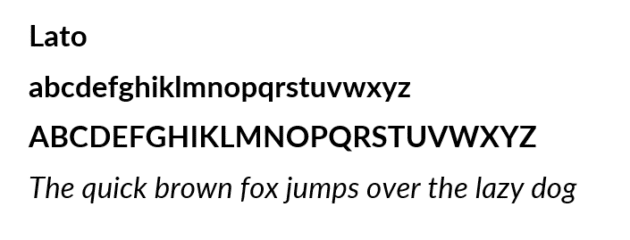
Lato เป็นหนึ่งในฟอนต์ที่ดีที่สุดที่จะใช้หากเว็บไซต์ของคุณเปิดใช้งานในด้านที่รุนแรง เช่น การเงิน กฎหมาย หรือแม้กระทั่งการบัญชี ใช้งานง่าย แบบอักษรของเว็บไซต์นี้ถือเป็นแบบอักษรขององค์กรที่แสดงความเป็นมืออาชีพสูง Lato เป็นแบบอักษรที่ดีที่สุดสำหรับผู้ที่ต้องการวิธีที่ทันสมัยในการปรับปรุงการออกแบบเว็บไซต์ของตน
เฮลเวติก้า
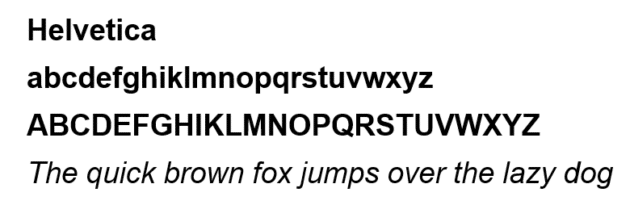
Helvetica เป็นหนึ่งในแบบอักษรเว็บไซต์ที่มีคนใช้มากที่สุดทั่วโลก ได้รับการออกแบบโดย Max Miedinger นักออกแบบชาวสวิส Helvetica ได้รับความนิยมเนื่องจากมีรูปแบบและขนาดที่หลากหลายอย่างไม่น่าเชื่อ ซึ่งช่วยให้นักออกแบบเลือกรุ่นที่ดีที่สุดสำหรับการสร้างสรรค์ของพวกเขาโดยเฉพาะ
เมอร์ริเวเธอร์
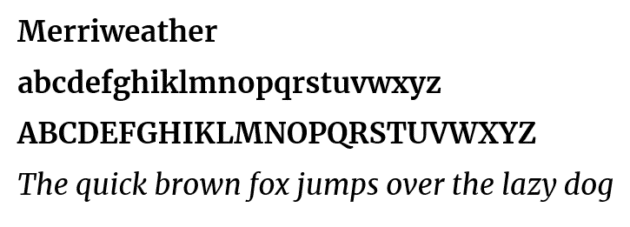
หากคุณมีผู้ชมที่หลากหลายที่อ่านเนื้อหาของคุณทั้งบนหน้าจอขนาดใหญ่และขนาดเล็ก แบบอักษรของเว็บไซต์ Merriweather คือสิ่งที่คุณต้องเลือก ฟอนต์สัดส่วนนี้ผสมผสานรูปลักษณ์ที่มีสไตล์เข้ากับความเรียบง่ายที่ลดลง เป็นการผสานที่น่าอัศจรรย์พร้อมศักยภาพมากมายสำหรับไซต์ในด้านต่างๆ Merriweather เหมาะสำหรับสไตล์ที่เป็นทางการและไม่เป็นทางการ
การแสดงเพลย์แฟร์
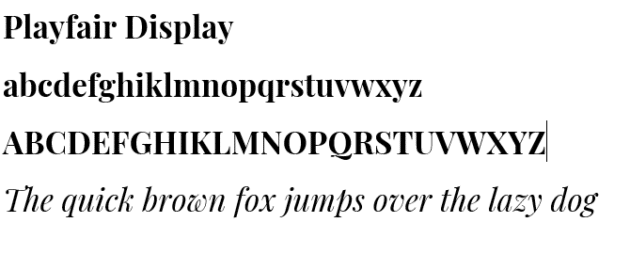
Playfair Display เป็นแบบอักษรที่มีสไตล์และมีลักษณะคลาสสิกเล็กน้อย หากคุณเลือกแบบอักษรสำหรับเว็บไซต์ที่ซับซ้อน Playfair Display คือตัวเลือกของคุณอย่างแน่นอน เหมาะอย่างยิ่งสำหรับเว็บไซต์ที่เบาและสวยงามพร้อมเนื้อหาที่เข้าใจง่าย แท้จริงแล้ว Playfair Display นั้นไม่สามารถอ่านได้เหมือนกับฟอนต์อื่นๆ ข้อได้เปรียบหลักของมันคือคลาส
มอนต์เซอร์รัต
ฟอนต์ sans serif นี้เกือบจะเป็นฟอนต์เว็บไซต์ที่ดีที่สุดที่คุณสามารถเลือกได้ โดยทั่วไปแล้วรูปแบบทางเรขาคณิตจะช่วยให้คุณสามารถหาวิธีนำไปใช้บนเว็บไซต์ของคุณได้ แม้ว่ามอนต์เซอร์รัตจะมีสไตล์มาก แต่ผู้คนจำนวนมากพบว่าสามารถอ่านได้ทั้งบนหน้าจอขนาดเล็กและขนาดใหญ่
ลิเบอร์ บาสเกอร์วิลล์
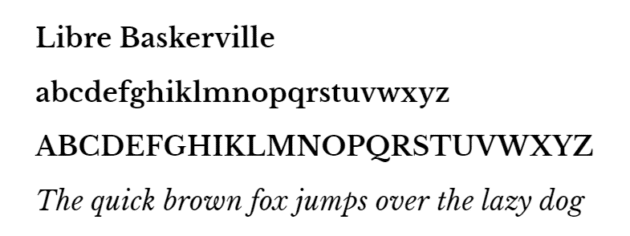
Libre Baskerville เป็นฟอนต์เซอริฟที่ได้รับแรงบันดาลใจจากบรรพบุรุษในศตวรรษที่ 18 สไตล์คลาสสิกเหมาะสำหรับการใช้งานในด้านต่างๆ เช่น เศรษฐกิจ กีฬา และความงาม แม้ว่า Libre Baskerville จะเป็นที่นิยมมาก แต่ก็ไม่ใช่ตัวเลือกที่ดีที่สุดหากผู้ชมของคุณใช้หน้าจอขนาดใหญ่เพื่อเข้าถึงเว็บไซต์ของคุณ เนื่องจากแบบอักษรจะดูไม่ดีนักเมื่อขนาดของมันใหญ่เกินไป
คอเดกซ์
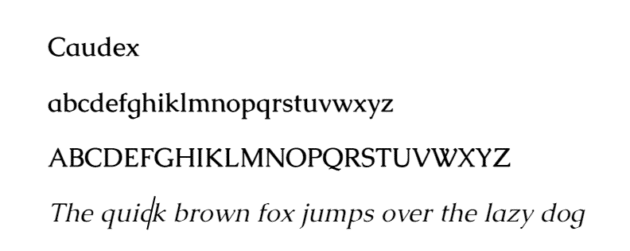
เดิมใช้ในต้นฉบับยุคกลาง Caudex ได้รับการปฏิรูปและปรับให้เข้ากับความเป็นจริงของเราในช่วงปลายยุค 90 และไม่ได้หยุดการพัฒนาตั้งแต่นั้นเป็นต้นมา Caudex สามารถใช้กับทั้งย่อหน้าและหัวเรื่อง และไม่ต้องสงสัยเลยว่าเป็นแบบอักษรที่มีรูปแบบหลากหลายมากที่สุด เหมาะสำหรับการใช้งานทั้งหน้าจอขนาดใหญ่และขนาดเล็ก
บาร์โลว์
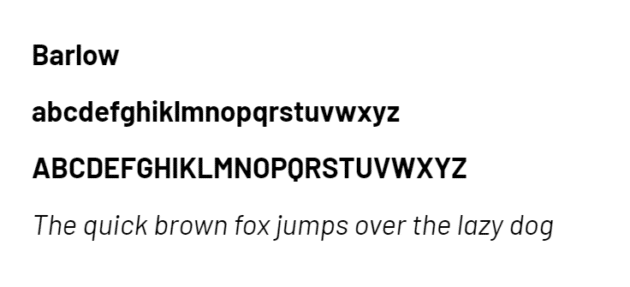
ฟอนต์ sans serif Barlow นี้ดูเหมือนจะได้รับแรงบันดาลใจจากป้ายทะเบียนแคลิฟอร์เนียและป้ายทางหลวง การออกแบบที่สะอาดตาสามารถเพิ่มความราบรื่นให้กับเว็บไซต์ของคุณ ทำให้มีบรรยากาศสบาย ๆ และอ่านง่าย ข้อดีอีกอย่างของแบบอักษรนี้คือความเข้ากันได้กับแบบอักษรอื่นๆ มากมายที่สามารถพบได้บนเว็บไซต์ของคุณ
โรบอท
เรียบง่ายเป็นคำคุณศัพท์ที่อธิบายแบบอักษร Roboto ได้อย่างสมบูรณ์แบบ จุดประสงค์หลักคือเพื่อส่งข้อมูลให้กับลูกค้าของคุณโดยไม่มีรูปแบบที่ซับซ้อน ถือว่าเป็นฟอนต์มืออาชีพ แต่ก็มีบางกรณีที่ผู้ออกแบบใช้ฟอนต์นี้สำหรับเนื้อหาที่เป็นมิตร
วิธีการเลือกแบบอักษรที่เหมาะสม?
แบบอักษรที่เหมาะสมมักเป็นกุญแจสำคัญสำหรับผู้ใช้เว็บไซต์จำนวนมาก ดังนั้น การที่นักออกแบบสามารถเลือกได้อย่างถูกต้องจึงส่งผลดีต่อประสบการณ์ของผู้ใช้และคำวิจารณ์ของพวกเขา
เลือกฟอนต์ตามเนื้อหาของเว็บไซต์
ไม่ใช่เรื่องที่เป็นความลับ โดยส่วนใหญ่แล้ว ส่วนที่ใหญ่ที่สุดของเว็บไซต์ของคุณจะประกอบด้วยข้อความประเภทต่างๆ ดังนั้น หากคุณต้องการเว็บไซต์ที่มีสไตล์และมีการจัดเรียงที่ดี ขั้นตอนแรกในการทำให้สำเร็จคือการเลือกแบบอักษรที่เหมาะสมสำหรับข้อความนั้น เคล็ดลับที่ดีที่สุดสำหรับคุณคืออย่าใช้ฟอนต์มากกว่า 3-4 ฟอนต์ในหน้าเดียว มันจะดูแย่และยุ่งเหยิง ด้วยเหตุนี้ เนื่องจากมีฟอนต์ให้เลือกมากมาย คุณจึงควรเลือกฟอนต์ที่ดีที่สุดสำหรับคุณโดยเฉพาะ อย่ากดดันจนเกินไป
- คุณรู้อยู่แล้วว่าเหตุผลหลายประการว่าทำไมแบบอักษรจำนวนมากในเว็บไซต์เดียวจึงเป็นสิ่งที่แย่ที่สุดที่คุณสามารถทำได้ และนี่ก็เป็นอีกเหตุผลที่ติดไว้ 2-3 อัน แบบอักษรที่มากขึ้นหมายถึงข้อมูลจำนวนมากที่ต้องประมวลผลและต้องใช้เวลา
- อย่าออกแบบให้ซับซ้อนเกินไปด้วยสิ่งที่สวยงามแต่ไร้ประโยชน์ซึ่งมีแต่จะทำให้แย่ลง ตัวอย่างเช่น เป็นสิ่งที่ดีที่จะใช้แบบอักษรที่ออกแบบมาอย่างดีสำหรับชื่อเรื่องและหัวเรื่อง แต่สำหรับข้อความเนื้อหา การเลือกแบบอักษรพื้นฐานเช่น Robotica หรือ Helvetica นั้นสมเหตุสมผลกว่า